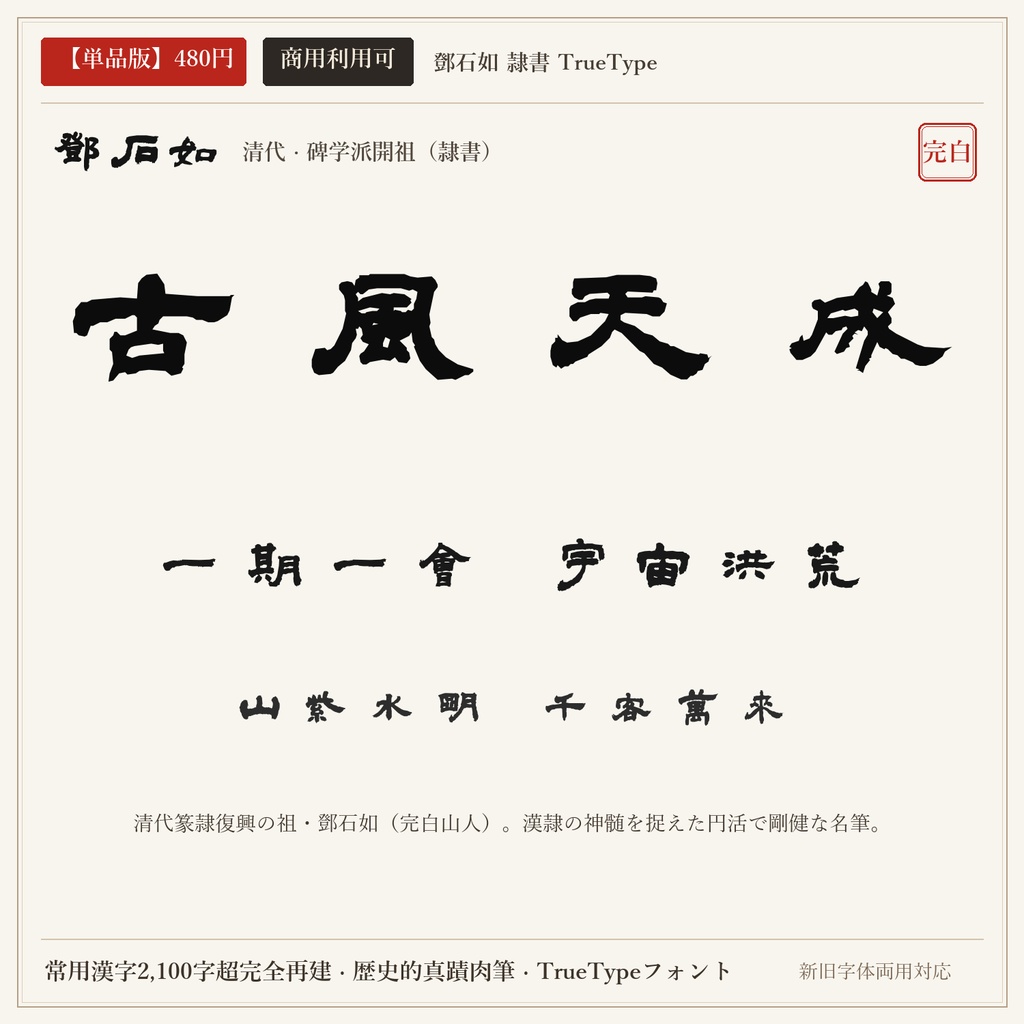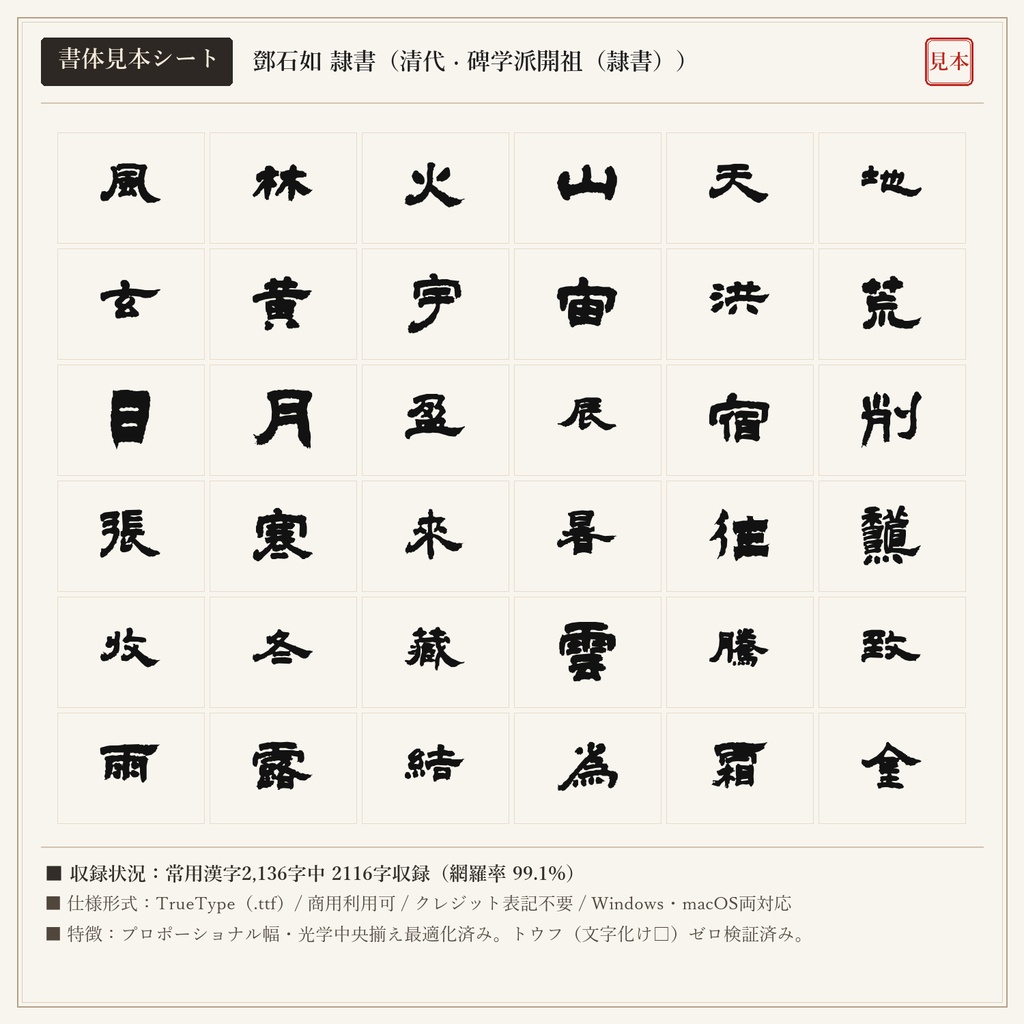
【単品版】鄧石如 隷書フォント|完白山人・篆隷の神髄・金石気・商用利用可
「完白山人」と号した清代碑学派の開祖・鄧石如の隷書から制作したフォントです。漢代の石碑を徹底して自家薬籠中の物とし、篆書の円やかな筆力と隷書の波磔を融合させた雄渾剛健な隷書です。 ■ 本フォントの特徴 ・常用漢字2,136字中、2116字を高精度収録(網羅率 99.1%)。 ・現代の新字体を入力しても、歴史的な真蹟字形・旧字体が自然に出力されるデュアルマッピング対応。 ・文字ごとの最適なプロポーショナル字幅設定により、自然で流麗な連綿と墨の息遣いを再現。 ・トウフ(文字化け□)を出さない事前フォントマッピング検証済み。 ■ 未収録文字一覧(全20字) 歴史的真蹟・拓本に存在しない以下の字種は未収録(非対応)となります。ご購入前にご確認ください。 刹 厘 唄 堀 峠 扱 拶 枠 栃 桁 濫 碁 線 繰 脊 菓 著 認 込 酎 ■ 形式 TrueTypeフォント(TTF) / Windows・macOS両対応 ■ 利用規約 個人・法人の商用利用OK。クレジット表記不要。 ロゴ、動画、ゲーム、書籍、同人誌、配信サムネイル、Web、印刷物、グッズ等に自由にご使用いただけます。 フォントファイル自体の再配布・共有・販売・転売は禁止です。 ※東晋の王羲之(行書)と盛唐の顔真卿(楷書)を同梱した「【無料版】王羲之 + 顔真卿 2書体セット(0円)」もショップ内にて無料配布中です。